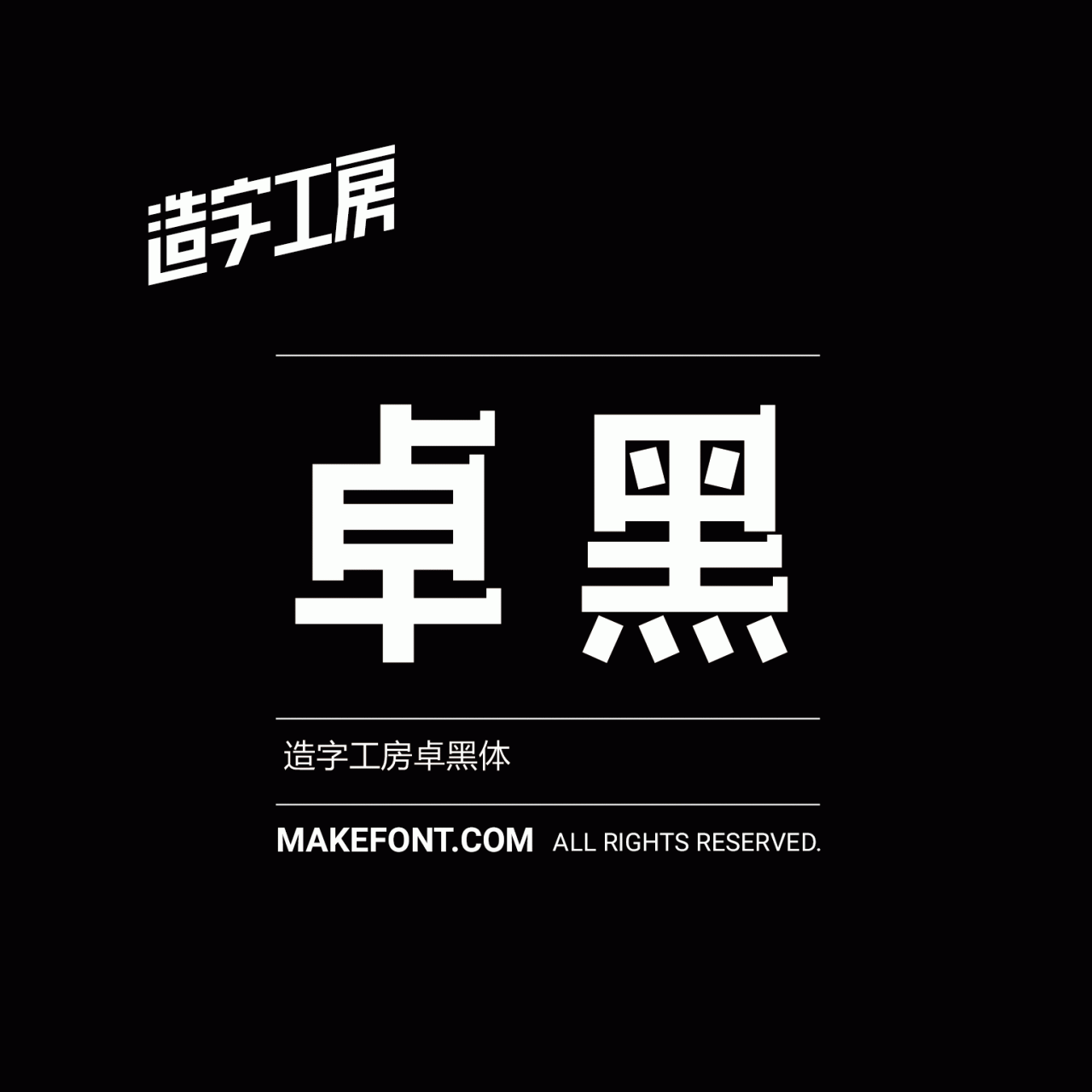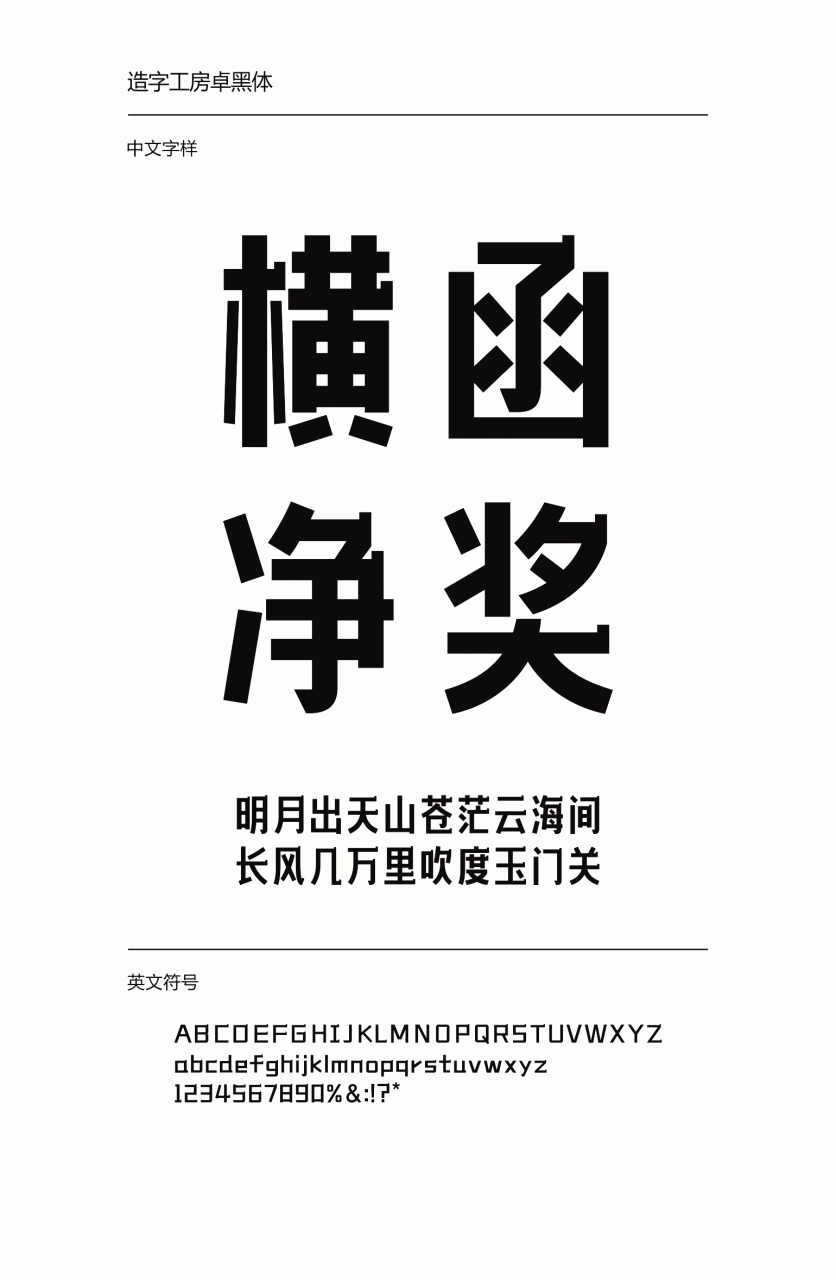
造字工房卓黑常规体设计说明
造字工房卓黑体,字形瘦长,笔画平直,其风格雄强正肃,引人注目。字形结构严谨,实用性强,横画上的方形凸起处理,令字形个性鲜明,更显凝练正则之势。适用于大标题及个性品牌设计推广等环境。本字体为简体字库,采用OpenType/CID格式,Adobe-GB1-5编码。基于中华人民共和国GB2312-80字符集标准,另按需添加101个汉字。共收容字数6864CJK汉字,ASCII常用字符100个。